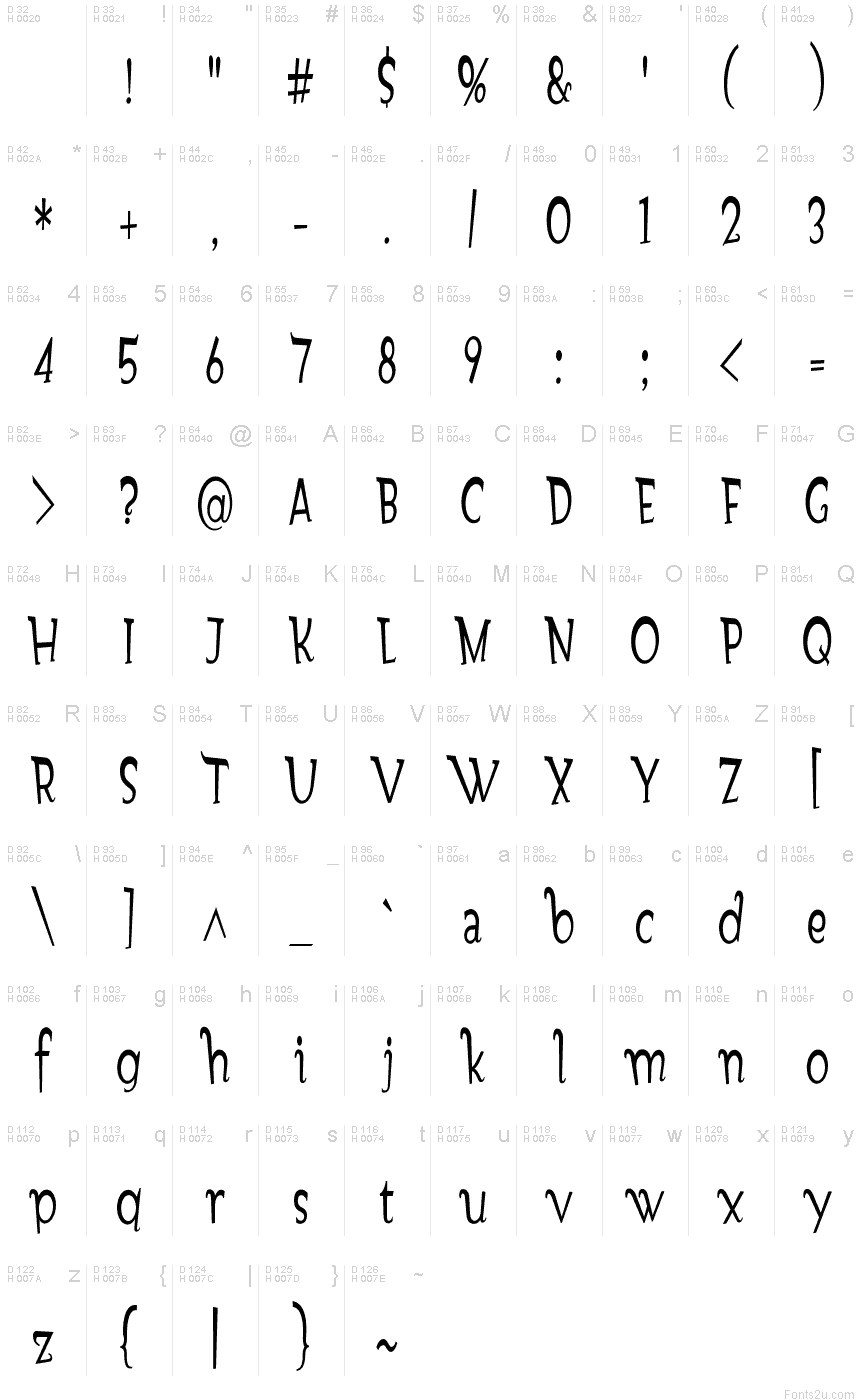
Gondoliere
Gondoliere di CybaPee Creations è un font display gratuito in stile fumetto, caratterizzato da un tratto libero e disegnato a mano. Ogni lettera si inclina e oscilla come se cavalcasse un'onda, con tratti a inchiostro che si allargano e si assottigliano in punti inaspettati. Le forme sono giocose ma non infantili, regalando ai titoli e alle frasi brevi un carattere affascinante e leggermente fuori dagli schemi.
Usando Gondoliere, puoi dare personalità a poster, fanzine, inviti, loghi di brand indipendenti, copertine di libri per bambini e grafiche social originali. Il ritmo alto e vivace aiuta le parole brevi a risaltare, specialmente nelle dimensioni più grandi. Questo font gratuito si abbina perfettamente a un sans serif geometrico ed essenziale per il testo principale, lasciando a Gondoliere il compito di gestire i momenti divertenti e d'impatto, mentre il font di supporto assicura la leggibilità.